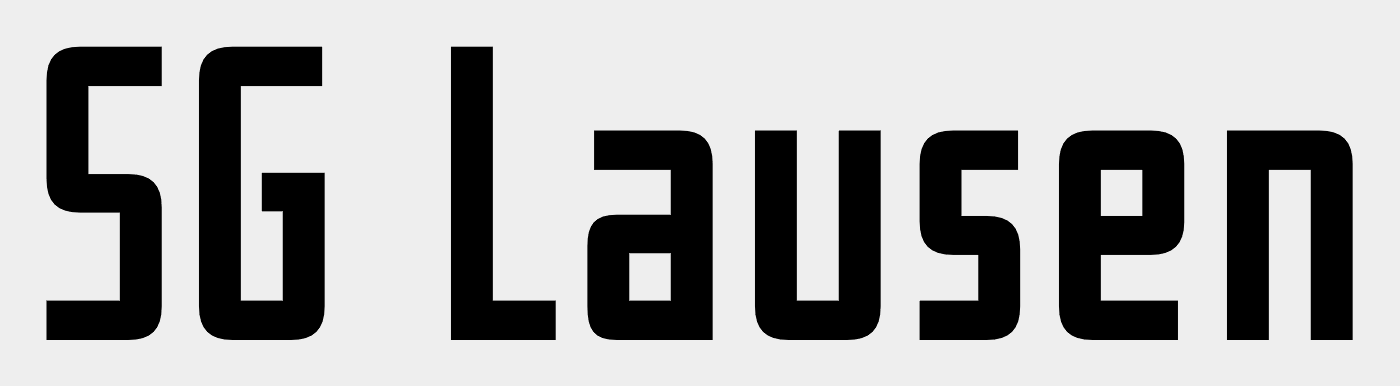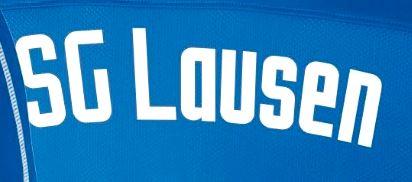
Suche Schriftart von Fußballtrikot SG Lausen
Hallo, bin fast am verzweifeln!!! Kennt jemand von Euch diese Schriftart?
Das ist entweder selbst gemacht – mit Lineal und Zirkel – oder ein irgendein Freefont ziemlich zweifelhafter Qualität, der, weil er so schlecht ist, dann auch nicht weitgehend bekannt sein wird.
Du hast jetzt zwei realistische Optionen: Mach es auch selbst (aber besser) oder nimm eine vernünftige Schrift ähnlicher Anmutung. Die Unterschiede werden niemandem bewusst auffallen.
Ich würde bei 11teamsports.com fragen, von dort sind die Trikots.
Helmut Lortz pflegte mit so einer Art von Brutalismus (Formteile: Quadrat und Viertelkreis) als Übungsaufgabe Studenten gerne optische Gesetzmässigkeiten bei Schriften bewusst zu machen (… Erkennen warum Balkenstärken und Rundungen optisch ausgeglichen werden müssen)
PS: Wobei mir der didaktische Sinn dieser Aufgabe (ja, wurde auch damit traktiert) eigentlich bis heute verborgen geblieben ist bzw. erst nach Lektüre der Quelle der Abbildung (Helmut Lortz, der Lehrer – Publikation der Hochschule der Künste Berlin) klar gemacht wurde, ähem. Aber als Kochrezept so im Sinne von »Fünf-Minuten-Gerichte« funktioniert es sicher ganz gut ;-)
Vielen Dank für Eure Hilfe! Habe eine "fast identische" Freefont namens "Emma 65" gefunden.